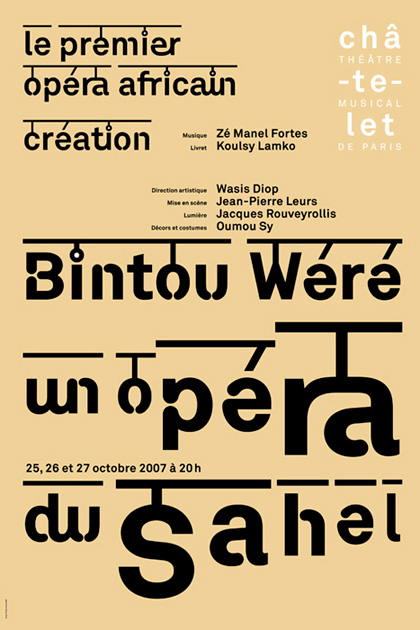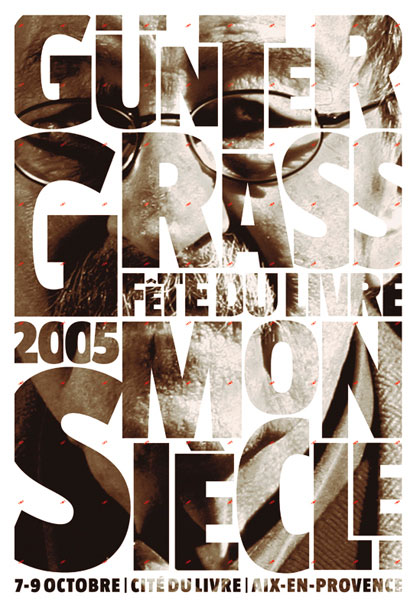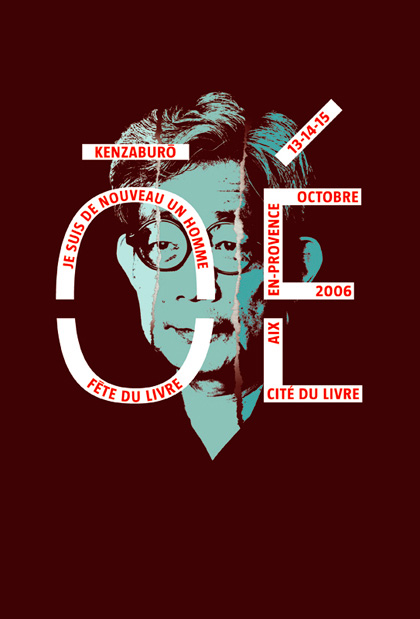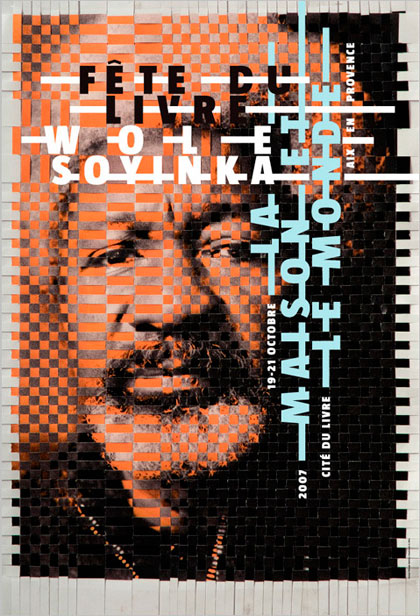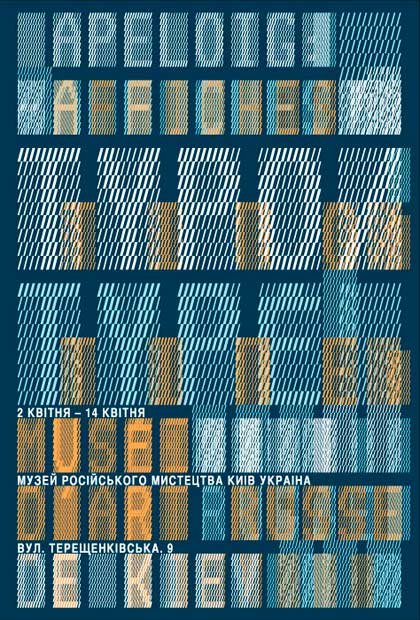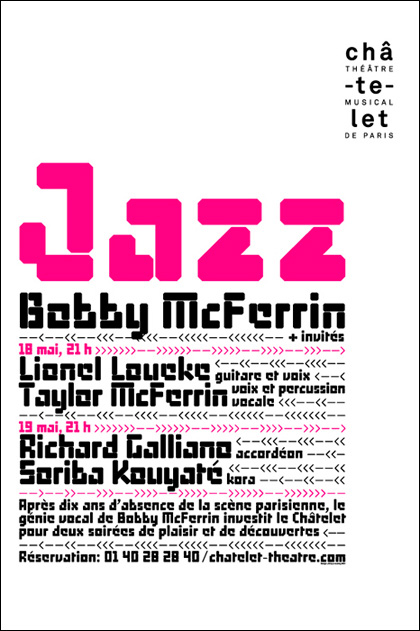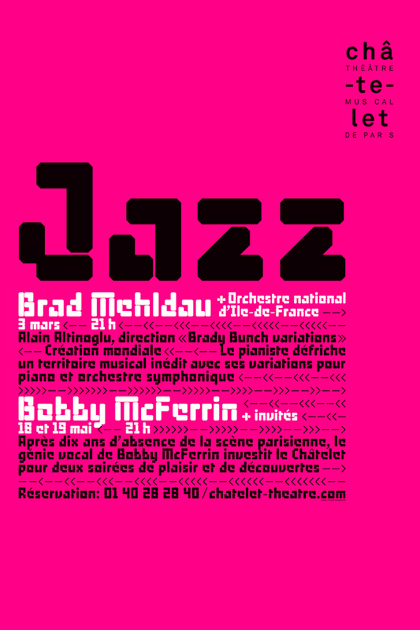
Philippe Apeloig | Exposition d’affiches et de lettres animées | Vivo in Typo
Philippe
Apeloig
Vivo in Typo
Exposition
d’affiches
et de lettres
animées
12 avril – 25 mai 2008
Espace Topographie de l’Art
La typographie relève non seulement d’un procédé permettant de reproduire un texte, mais aussi de la «manière» dont ce texte est imprimé : type des caractères utilisés, mise en pages, etc. Il s’agit autant de technique que de recherche artistique.
Sa spécificité tient, d’une part, à son appréciation au-delà des ateliers, galeries et musées, dans la rue, par le biais d’enseignes, publications ou affiches, et d’autre part à son mode de création, lié à une commande.
Certains caractères typographiques auxquels nous sommes aujourd’hui parfaitement habitués, tels Times New Roman, Futura, Helvetica et Univers, ont été élaborés parallèlement aux mouvements artistiques qui jalonnent notre histoire. Ils démontrent le questionnement et la recherche de certains artistes sur la perception et l’usage de l’écriture.
L’espace Topographie de l’Art présente Vivo in Typo, une exposition de travaux développés depuis une vingtaine d’années par le graphiste français Philippe Apeloig. Intégrant un ensemble de 30 affiches et une vidéo, l’exposition permet de partager sa passion pour les lettres considérées «non seulement comme véhicule de la pensée, mais aussi comme matière à création» [1].
Certaines affiches ont été réalisées pour des institutions comme le Musée du Louvre, le Musée d’Orsay et le Théâtre du Châtelet; d’autres pour des manifestations culturelles comme le Festival de danse et de musique Octobre en Normandie et la Fête du Livre en Aix-en-Provence.
Ces réalisations donnent à voir l’ingéniosité du graphiste dans son utilisation de l’image et du mot à travers un style épuré et minimaliste. La vidéo quant à elle dévoile son inventivité dans la création des caractères typographiques où se côtoient tradition et modernité.
Il s’agit toujours de concilier fonctionnalité et recherche artistique.
«La vocation du graphiste s’apparente à celle d’un acteur qui a pour mission de créer un personnage et de déclamer le texte d’un auteur de la façon la plus claire et la plus personnelle qui soit» [2].
[1] Philippe Apeloig in Au coeur du mot, Editions Lars Müller, Baden,Suisse, 2000.
[2] Ibid._
Bintou Wéré, le premier opéra africain
Théâtre du Châtelet, Paris
Sérigraphie, 100 x 150cm, 2007
Jazz
Bobby McFerrin et invités
Théâtre du Châtelet, Paris
Sérigraphie, 100 x 150cm, 2007
Jazz
Brad Mehldau, Bobby McFerrin
Théâtre du Châtelet, Paris
Sérigraphie, 100 x 150cm, 2007
Günter Grass, Mon Siècle
Fête du Livre, Aix-en-Provence
Sérigraphie, 118 x 175cm, 2005
Kenzaburo Oé, Je suis de nouveau un homme
Fête du Livre, Aix-en-Provence
Sérigraphie, 118 x 175cm, 2006
Wole Soyinka, La maison et le monde
Fête du Livre, Aix-en-Provence
Sérigraphie,118 x 175cm, 2007
Typo/Typé.
Affiche de l’Exposition Philippe Apeloig
Musée d’art russe, Kiev
Sérigraphie, 118 x 175 cm, 2005